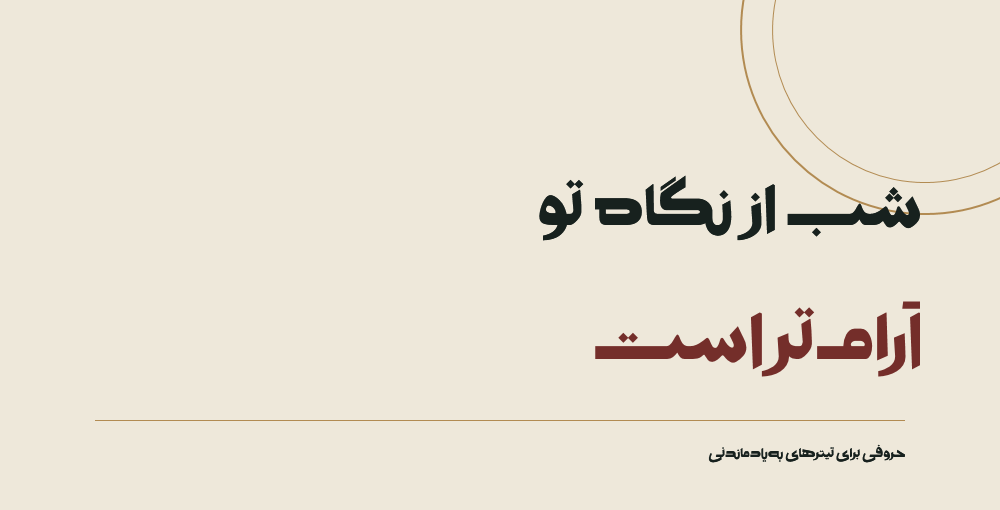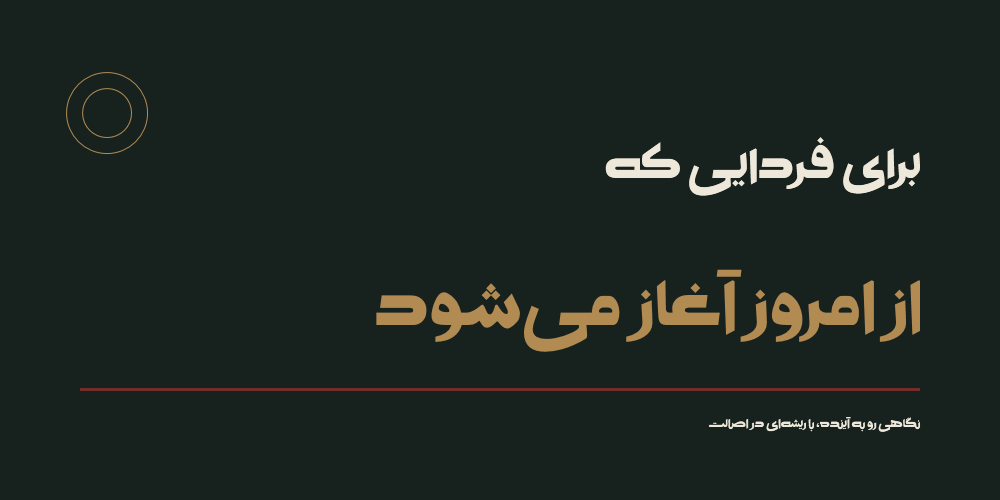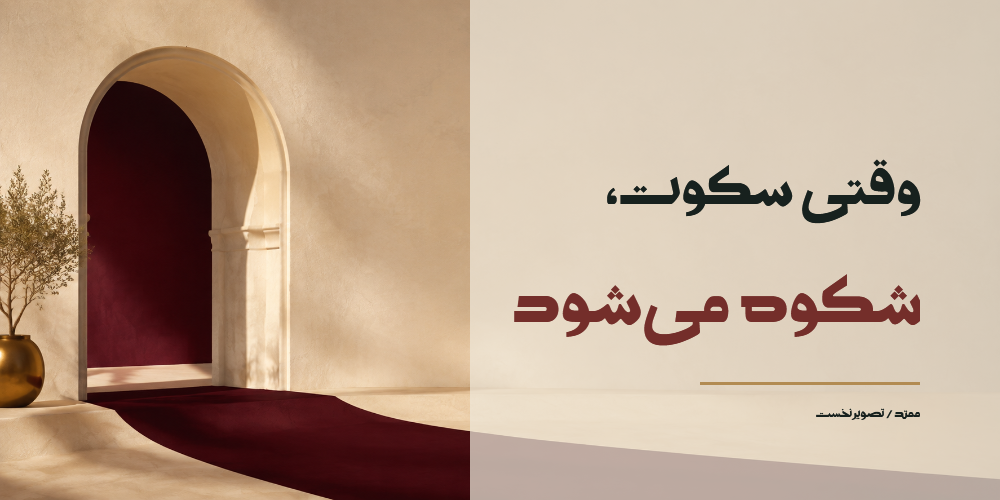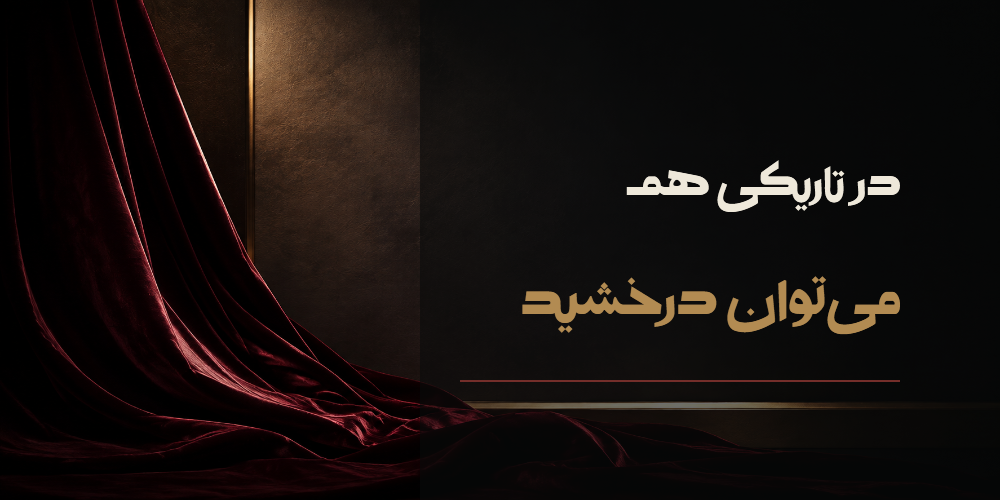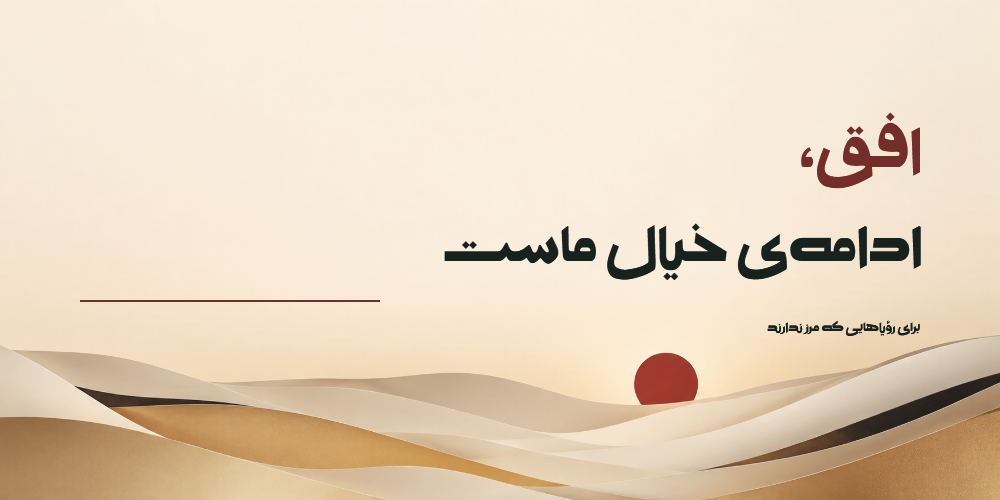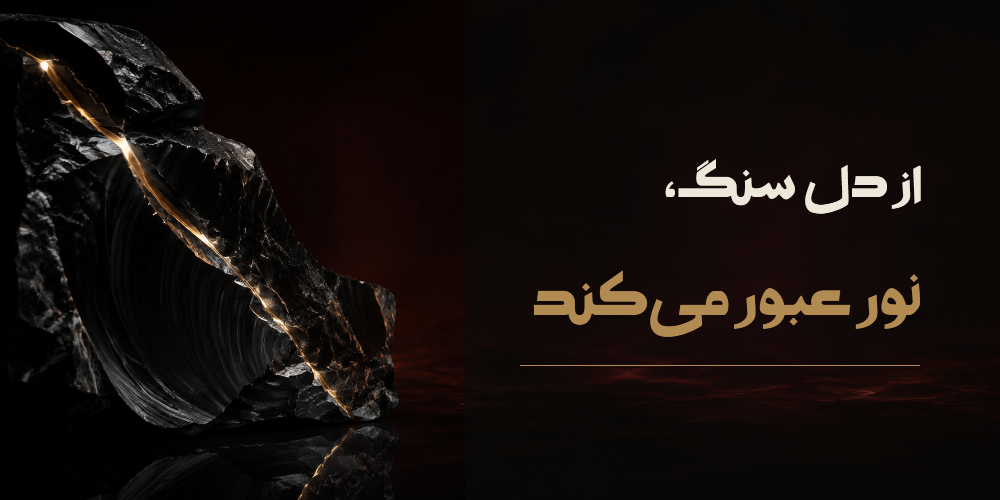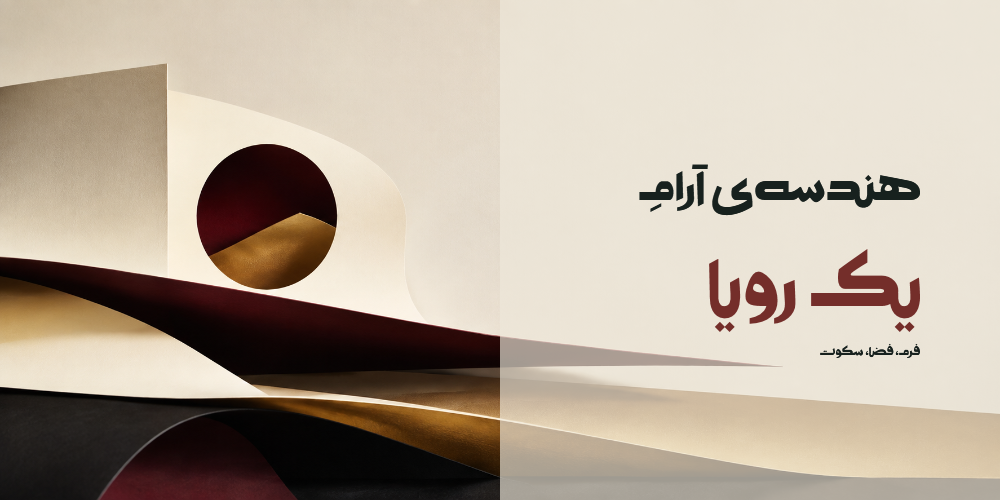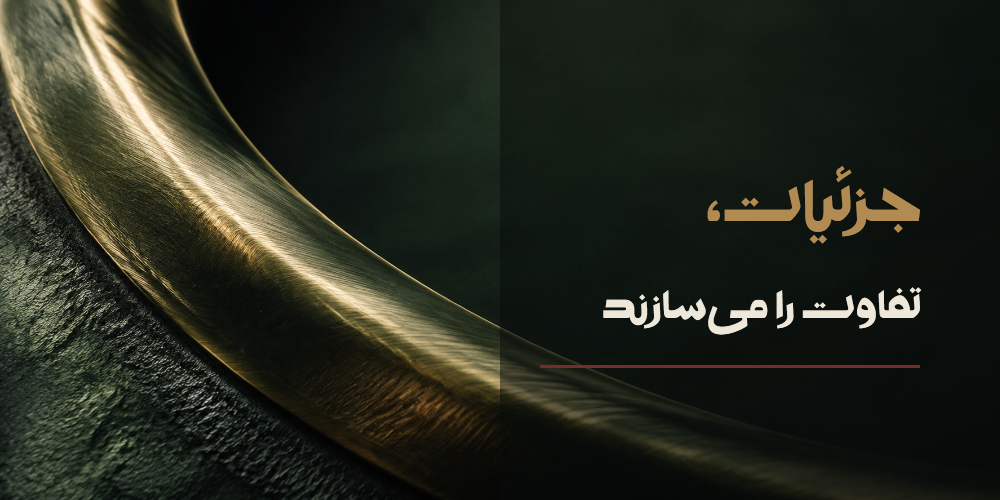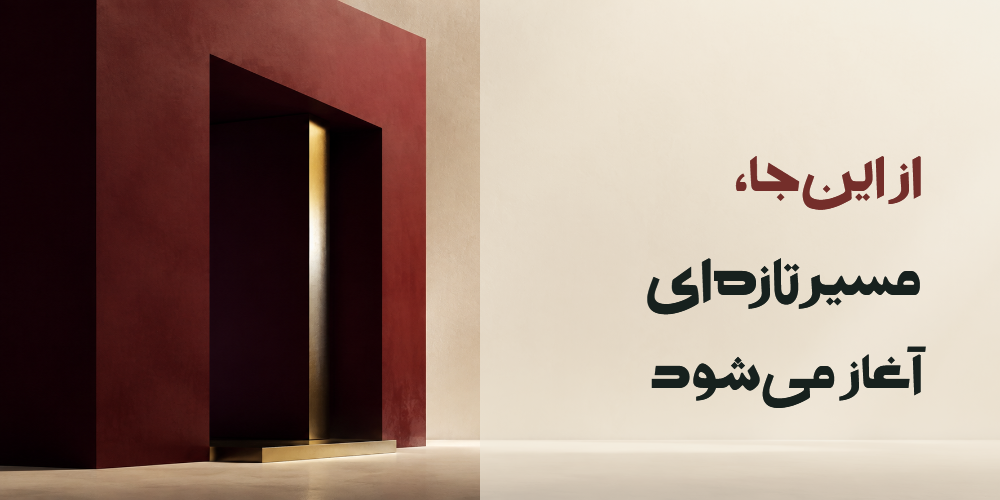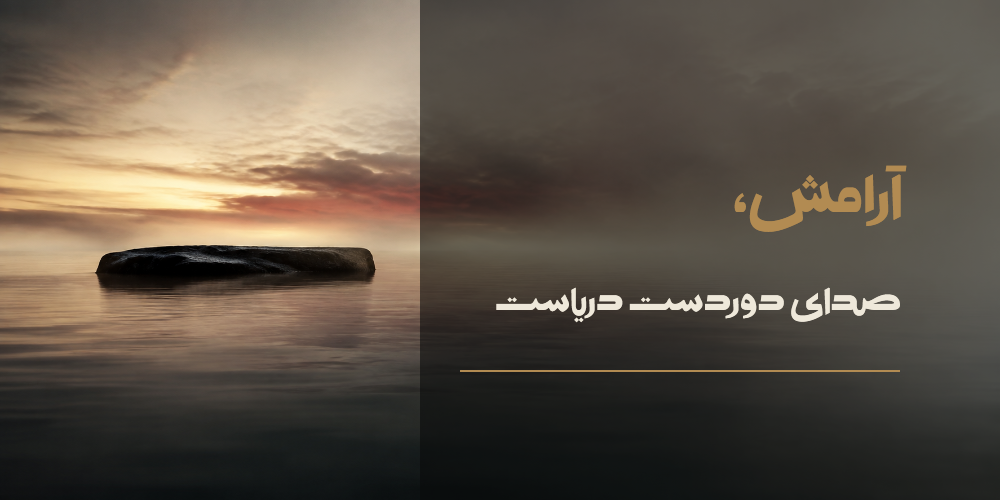
قلم ممتد font Momtad Bold
قلم ممتد
کاری از زینب ایزدیار
درباره قلم ممتد
فونت «ممتد بولد» قلمی نمایشی، جسور و متفاوت است که با کشیدگی‌های چشمگیر و ساختار هندسی خود، حضوری قدرتمند به واژه‌ها می‌بخشد. فرم خاص حروف باعث می‌شود تیترها حتی در ترکیب‌بندی‌های ساده نیز جلوه‌ای متمایز و به‌یادماندنی داشته باشند.
ممتد بولد انتخابی مناسب برای طراحی پوستر، جلد، تبلیغات، بسته‌بندی، هویت بصری، محتوای شبکه‌های اجتماعی و تیترهای کوتاه است. وزن سنگین و امتداد افقی حروف، فضای تصویر را به‌خوبی در اختیار می‌گیرد و امکان ساخت ترکیب‌های مدرن، جسورانه و خلاقانه را فراهم می‌کند.
این قلم بیش از آنکه برای متن‌های طولانی ساخته شده باشد، برای دیده‌شدن طراحی شده است؛ جایی که چند واژه باید با قدرت سخن بگویند، نگاه مخاطب را متوقف کنند و در ذهن باقی بمانند.
کاربردهای پیشنهادی
• طراحی پوستر و آثار تبلیغاتی
• تیتر مجلات، کتاب‌ها و جلد محصولات فرهنگی
• هویت بصری و طراحی لوگوتایپ
• بسته‌بندی محصولات
• بنرهای وب و کمپین‌های دیجیتال
• محتوای شبکه‌های اجتماعی
• جملات کوتاه و تایپوگرافی‌های نمایشی